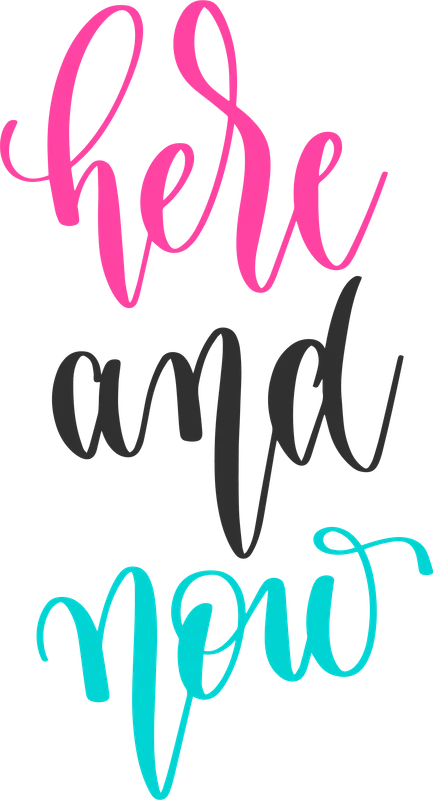
Chữ "here and now" font script màu hồng, xám, xanh
Chữ "here and now" font script màu hồng, xám, xanh — Thiết kế chữ "here and now" độc đáo với font script mềm mại, ba màu sắc nổi bật: hồng, xám, xanh. Phù hợp in áo, túi tote, sticker.
Trong hình có: chữ viết
Phong cách: script · Cảm giác: cool
Tông màu chủ đạo: hồng, xanh ngọc